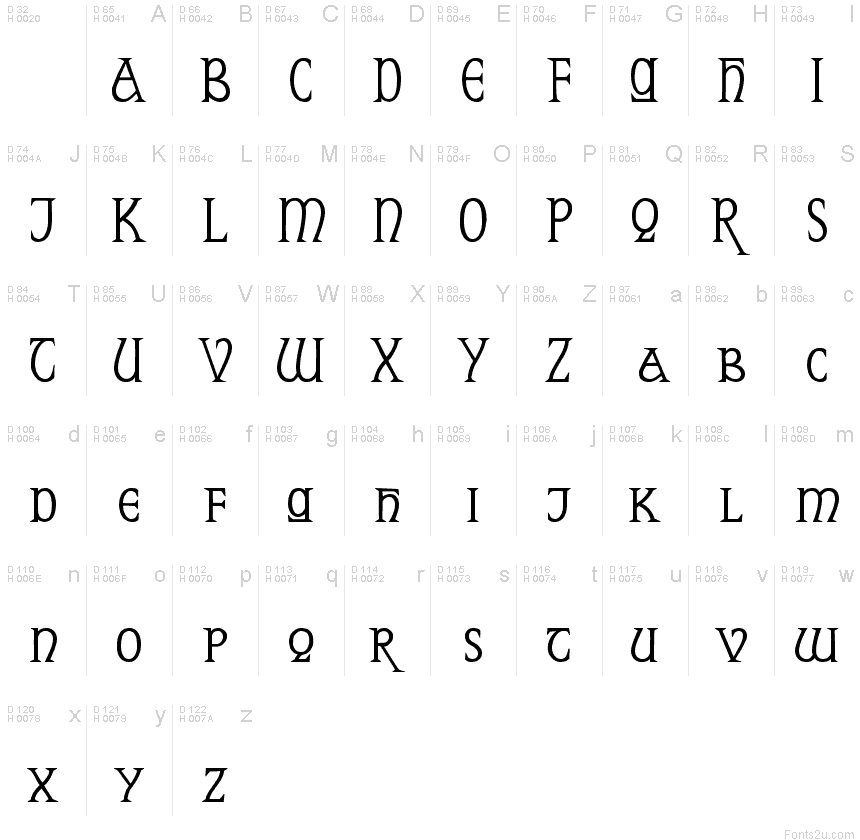
Reynard, darmowy font display w stylu retro autorstwa Davida F. Nalle’a, nawiązuje do klimatu późnego secesyjnego wzornictwa dzięki wysokim, zwężanym literom i ostrym, kaligraficznym łączeniom. Krój jest elegancki, a zarazem nieco przewrotny: zakrzywione linie zbiegają się w cienkie punkty, a wielkie litery mają w sobie teatralną, plakatową pewność siebie.
Świetnie sprawdza się na okładkach książek, w eleganckich opakowaniach, brandingu inspirowanym dawnymi epokami, menu kawiarnianym czy kartach tytułowych, gdzie darmowy krój może wnieść klimat minionych lat, nie będąc przy tym zbyt przytłaczającym. Wykorzystaj go również w krótkich nagłówkach, inicjałach lub monogramach – długie krzywe i strzeliste detale dodają krótkim słowom wyrazistego charakteru.